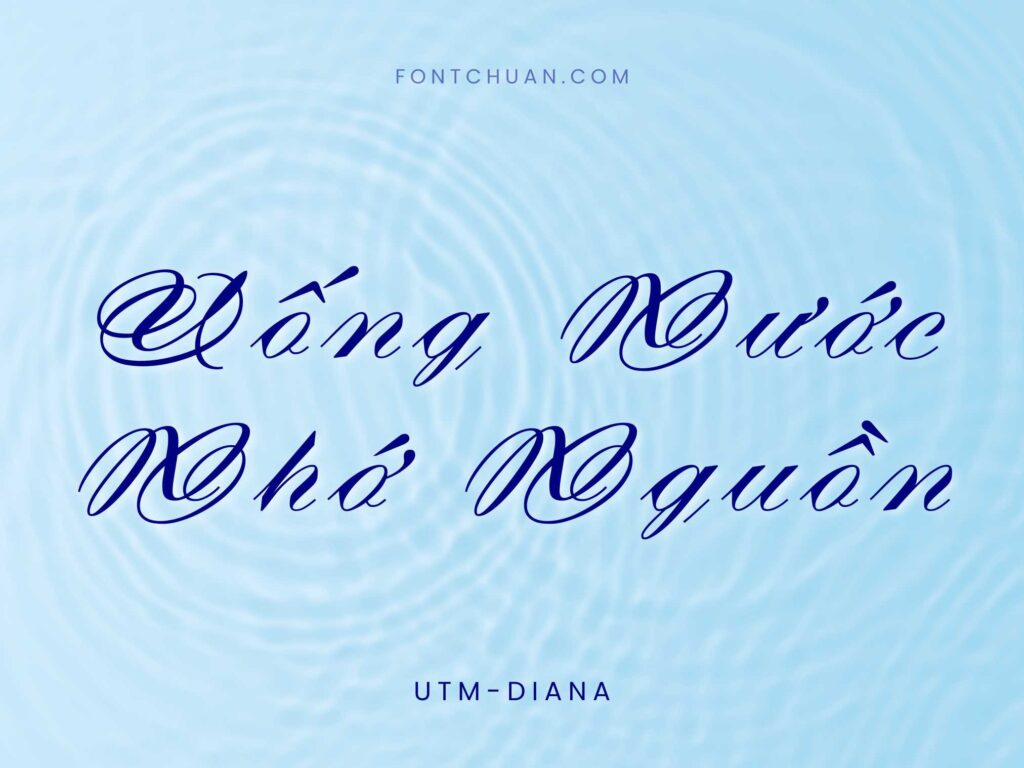
Font UTM Diana Việt Hóa
Việt hóa bởi: Thiên Minh
Font UTM Diana Việt Hóa là một kiểu chữ script thanh lịch, mang phong cách viết tay mềm mại và uyển chuyển. Với nét chữ mượt mà, độ dày linh hoạt và phong cách nữ tính, font này là sự lựa chọn hoàn hảo cho các thiết kế mang phong cách nghệ thuật, tinh tế và đầy cảm xúc. Đặc biệt, UTM Diana còn có thể ứng dụng như một Font chữ ký, giúp tăng thêm nét cá nhân hóa và sự sang trọng cho các dự án thiết kế.
Font này đã được Việt hóa để hỗ trợ đầy đủ tiếng Việt bởi Thiên Minh, ngoài ra còn hỗ trợ hơn 200 ngôn ngữ khác. Thành viên của Font Chuẩn đã sưu tầm và chọn lọc font này nhằm đáp ứng nhu cầu của người dùng trong thiết kế và ứng dụng thực tế. Font có đặc điểm nổi bật với nét chữ uyển chuyển, giúp tạo điểm nhấn trong các dự án như thiệp cưới, bìa sách, quảng cáo thời trang và nhiều lĩnh vực sáng tạo khác.